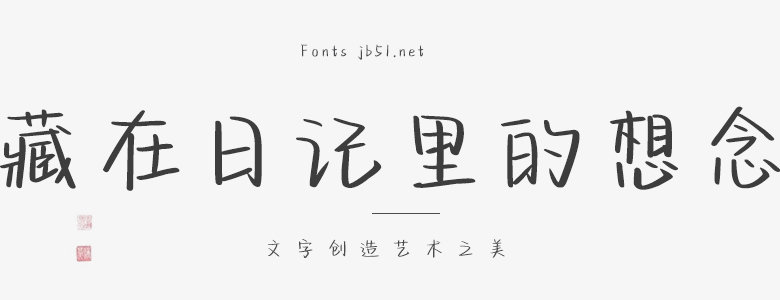
藏在日記里的想念
藏在日記里的想念”是一款獨特而富有情感的字體設(shè)計。這款字體充滿了手寫痕跡,仿佛每一筆都是一個故事,讓人在閱讀時感受到文字的溫度。其線條細膩而柔和,表現(xiàn)出想念的深度和復(fù)雜性,而字形中的一些細微變化則增添了更多的情感層次。 “藏在日記里的想念”字體的藝術(shù)性在于其獨特的書寫風(fēng)格。它不僅在視覺上引人注目,同時也引導(dǎo)讀者深入到文字所表達的情感世界。該字體的每一個字母都精心設(shè)計,注重細節(jié),以確保在任何文本中都能優(yōu)雅地展現(xiàn)。其藝術(shù)效果足以將任何普通文本提升為一件充滿情感和藝術(shù)性的作品。 總的來說,“藏在日記里的想念”字體是一份情感的獨特表達,它通過字體設(shè)計將文字和情感緊密結(jié)合,為讀者提供了一種全新的閱讀體驗。無論是用于個人項目還是商業(yè)用途,這款字體都是一個極好的選擇,能夠增強文本的情感深度,并觸動讀者的內(nèi)心。